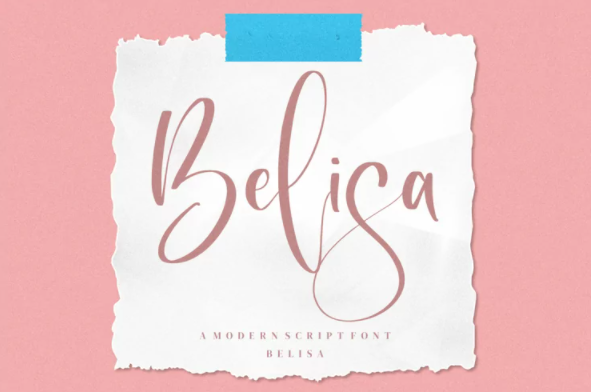
[Fontbundles] Belisa Font (2021)
Belisa- Modern Script Font, от Integritype Studio, это современный шрифт премиум-класса, подходящий для любых проектов, таких как: логотипы, брендинговые проекты, дизайн домашней одежды, упаковка продуктов, кружки, цитаты, плакаты, сумки, футболки, обложки книг, именные карточки, пригласительные открытки, поздравительные открытки, этикетки, фотографии, водяные знаки, специальные мероприятия и все другие роскошные проекты, которые нуждаются в премиальном фирменном вкусе.